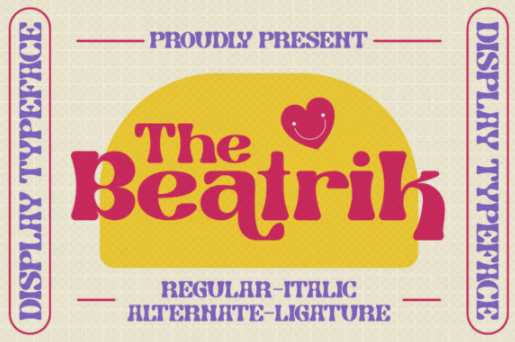
Creativefabrica The Beatrik Font 2021
[Creativefabrica] The Beatrik Font (2021)
Beatrik - это крутой, стильный и смелый шрифт с засечками.
Этот шрифт идеально подходит для элегантного и роскошного логотипа, дизайна названия книги или фильма, модного бренда, журнала, одежды, надписей, цитат и многого другого.